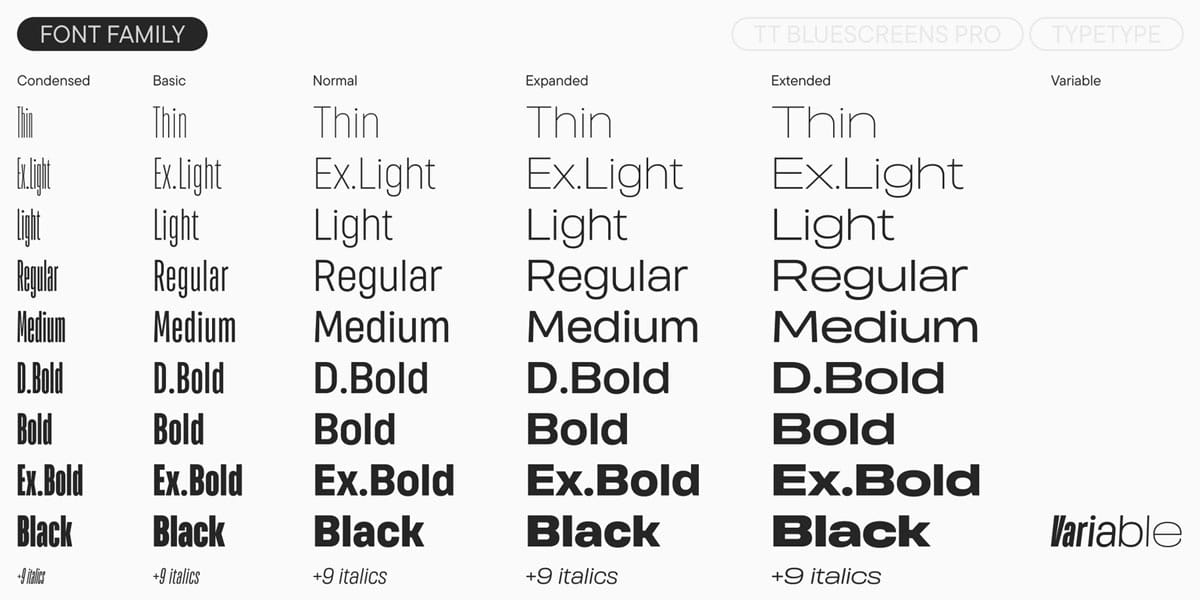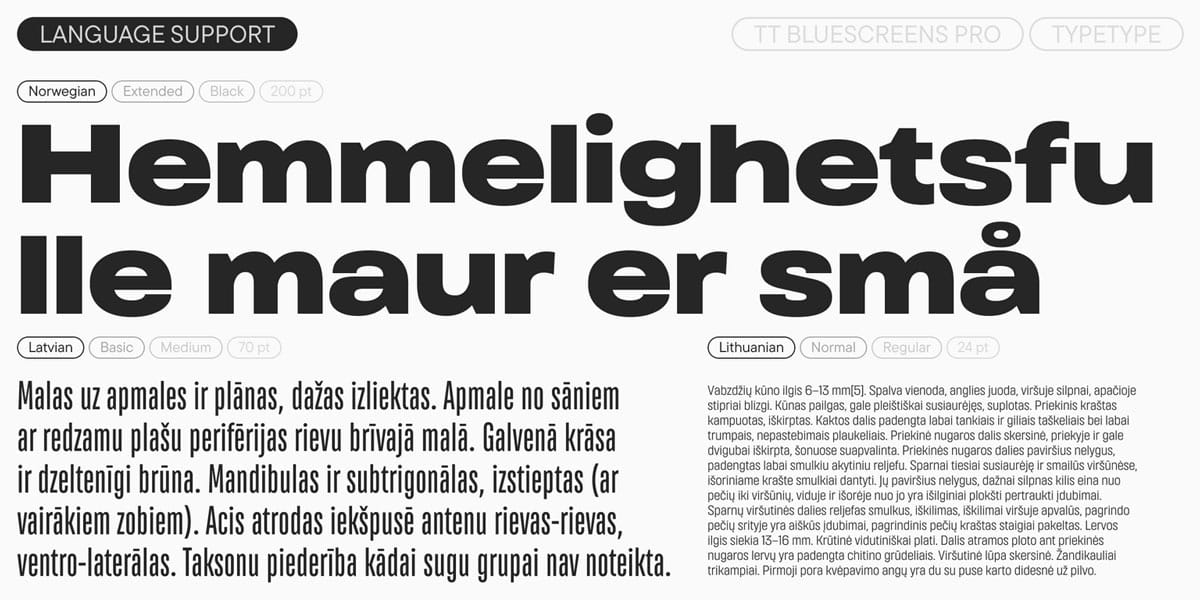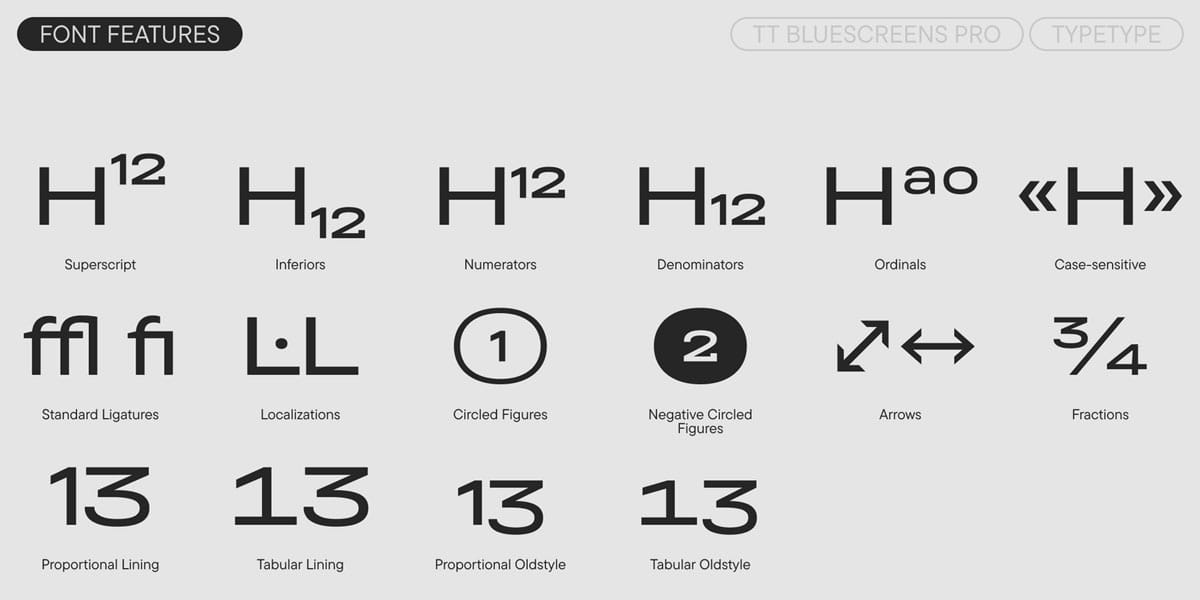
TT Bluescreens Pro 4.000: “màn hình xanh” đã tiến hoá thành hệ font đa độ rộng
Nếu bạn thích chất neo-grotesque gọn gàng nhưng vẫn có “chút cá tính” để nhận diện thương hiệu, TT Bluescreens Pro là một lựa chọn đáng cân nhắc – đặc biệt từ khi version 4.000 ra mắt với 5 subfamilies theo độ rộng (widths), giúp chữ “fit layout” linh hoạt hơn mà vẫn giữ đúng DNA của family.
TypeType mô tả TT Bluescreens Pro là một neo-grotesque có tỷ lệ hẹp (narrow proportions) dành cho display settings, mang cảm giác tinh tế nhưng dễ nhận diện – đủ mạnh cho headline, và vẫn đủ “neutral” để dùng trong nhiều bối cảnh thiết kế.
TT Bluescreens khởi đầu (2015) như một typeface phục vụ poster phim và film credits/disclaimers, nơi yêu cầu chữ phải rõ ràng, “đứng hình” tốt ở kích thước lớn và vẫn đọc ổn trong các dòng thông tin. Theo thời gian, TypeType tiếp tục mở rộng family để TT Bluescreens trở nên đa dụng hơn, và đến bản 4.000 (2026) đưa TT Bluescreens Pro thành hệ font 5 độ rộng cho rất nhiều bài toán layout.
| Số styles | 91 styles (45 upright + 45 italic + 1 variable) |
| Subfamilies (độ rộng) | 5 subfamilies: Condensed, Base (TT Bluescreens Pro), Normal, Expanded, Extended |
| Glyphs | 877 glyphs / style |
| OpenType features | 30 OpenType features |
| Ngôn ngữ | Hỗ trợ 240+ languages |
Update 4.000 có gì mới?
Bản TT Bluescreens Pro 4.000 mang lại thay đổi “đáng tiền” nhất: mở rộng hệ độ rộng để dùng từ narrow đến wide mà vẫn giữ DNA của family.
1) Family mở rộng lên 5 subfamilies, thêm 3 subfamily mới
Ở phiên bản 4.000, TypeType bổ sung 3 subfamily mới: Normal, Expanded và Extended – đồng thời variable font cũng được cập nhật để “gom” cả 5 độ rộng vào một hệ variable thống nhất.
- Normal – độ rộng “classic sans”, dễ dùng nhất cho đa số layout
- Expanded – rộng hơn, hợp branding/packaging cần cảm giác thoáng
- Extended – rất rộng, tạo vibe mạnh cho headline/poster
2) Từ 37 styles lên 91 styles
Số styles tăng mạnh giúp bạn có đủ lựa chọn weight + italic theo từng độ rộng, thay vì phải “chế” bằng scale ngang (dễ méo form và giảm chất lượng thị giác).
3) Variable font được nâng cấp (width axis thay đổi)
Điểm đáng chú ý trong 4.000 là hệ variable được cập nhật, trong đó Width variability axis đổi từ 75 | 100 | 100 sang 50 | 100 | 150, giúp range độ rộng rộng rãi hơn cho thiết kế.
4) Nâng cấp kỹ thuật: kerning, hinting, OpenType
- Kerning được cập nhật toàn bộ; hinting cũng được cập nhật
- OpenType features tinh gọn từ 31 → 30 do gộp một số stylistic sets (SS06 & SS01)
- Glyphs tăng nhẹ từ 874 → 877
TT Bluescreens Pro 4.000 là bản nâng cấp biến một typeface “narrow mang chất điện ảnh” thành một hệ font đa độ rộng dùng được cho rất nhiều thiết kế: branding, poster, packaging, cover và cả film credits/disclaimers. Nếu bạn cần một kiểu font neo-grotesque vừa gọn vừa có cá tính, nhưng vẫn đủ linh hoạt cho hệ thống layout hiện đại – đây là một lựa chọn rất đáng thử.